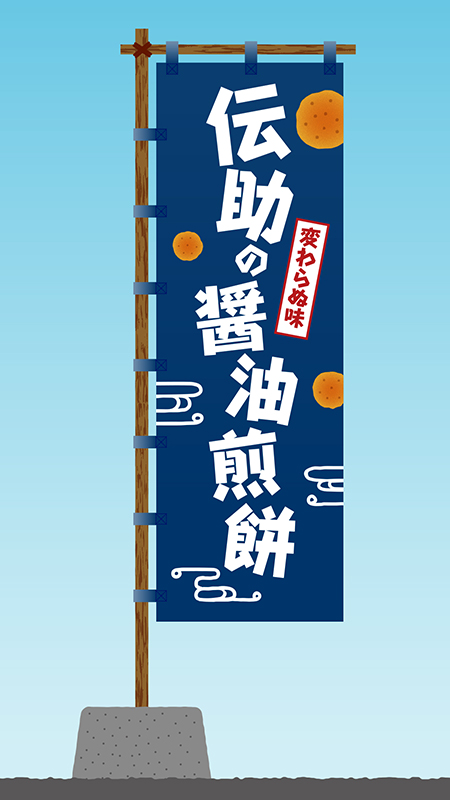
「竹」について
タイプデザイナーの竹下直幸氏がデザインしたフォントです。竹下氏は、モリサワでの勤務を経てタケノコ・デザインルームを設立。1993年に「モリサワタイプフェイスコンテスト」で銀賞を受賞し、そのフォントが「竹」としてリリースされました。
「竹」の特徴
「竹」は、文字の中で通常は曲線である部分を全て直線で構成した、独特なゴシック系スクリプト書体です。大胆なデザインですが、楷書の運筆も感じさせます。シンプルで均質なエレメントと、文字の自然な形の両方を兼ね備えたフォントです。
細いウエイトでは笹のような繊細なイメージになります。整然としたシャープな印象で、長文を組んでも可読性は損なわれません。太いウエイトでは強いインパクトを出すことができ、無骨ながらも親しみやすい雰囲気です。
作例ではノボリのデザインとしてインパクトを狙いたかったので、最も太いHウエイトを使いました。かな文字は漢字以上にカクカクしていて、とても面白い造形です。クセは強いですが実は使いやすく、雰囲気を出しやすい珍しいフォントだと思います。